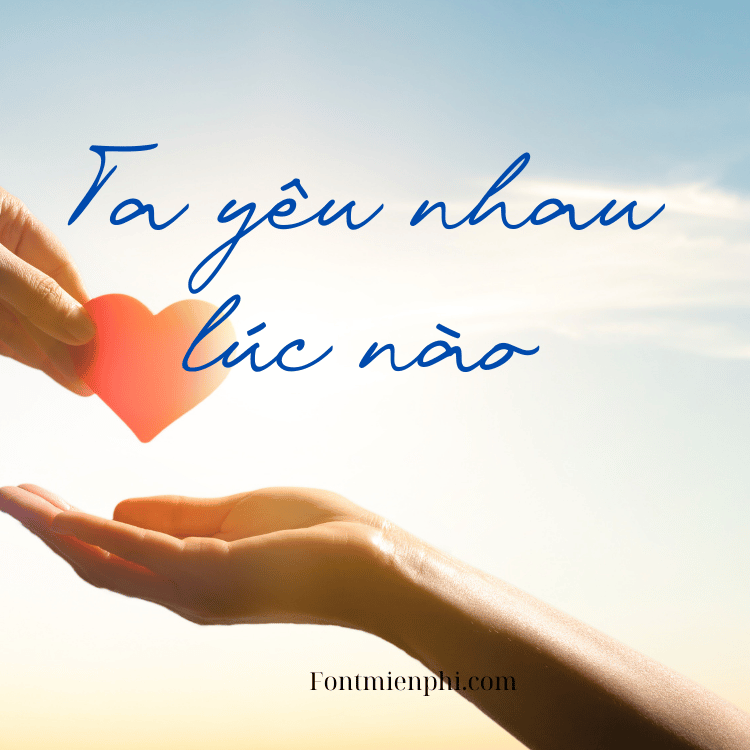
Tải Font việt hoá MJ Whitegone-Regular Miễn Phí Cho Thiết Kế Ấn Tượng
Giới thiệu về Font việt hoá MJ Whitegone-Regular
Trong thế giới đồ họa hiện đại, việc tìm kiếm một bộ Font Miễn Phí chất lượng luôn là ưu tiên hàng đầu của các bạn học sinh và giáo viên. Font việt hoá MJ Whitegone-Regular nổi bật như một lựa chọn hoàn hảo nhờ phong cách thanh lịch và hiện đại. Đây là bộ font được tinh chỉnh kỹ lưỡng về dấu tiếng Việt, giúp người dùng dễ dàng ứng dụng vào các bài thuyết trình, báo cáo học tập hay thiết kế thiệp mời mà không lo lỗi hiển thị. Với các đường nét dứt khoát nhưng không kém phần mềm mại, bộ chữ này mang lại cảm giác chuyên nghiệp cho mọi khung hình.
Đặc điểm nổi bật của Font việt hoá MJ Whitegone-Regular
Phong cách thiết kế tối giản
MJ Whitegone-Regular sở hữu cấu trúc chữ cái cân đối, giúp văn bản trở nên dễ đọc và thoáng mắt. Điều này cực kỳ quan trọng trong môi trường giáo dục, nơi thông tin cần được truyền đạt một cách rõ ràng nhất. Font việt hoá MJ Whitegone-Regular không chỉ đẹp mà còn giữ được sự trang trọng cần thiết cho các tài liệu học thuật.